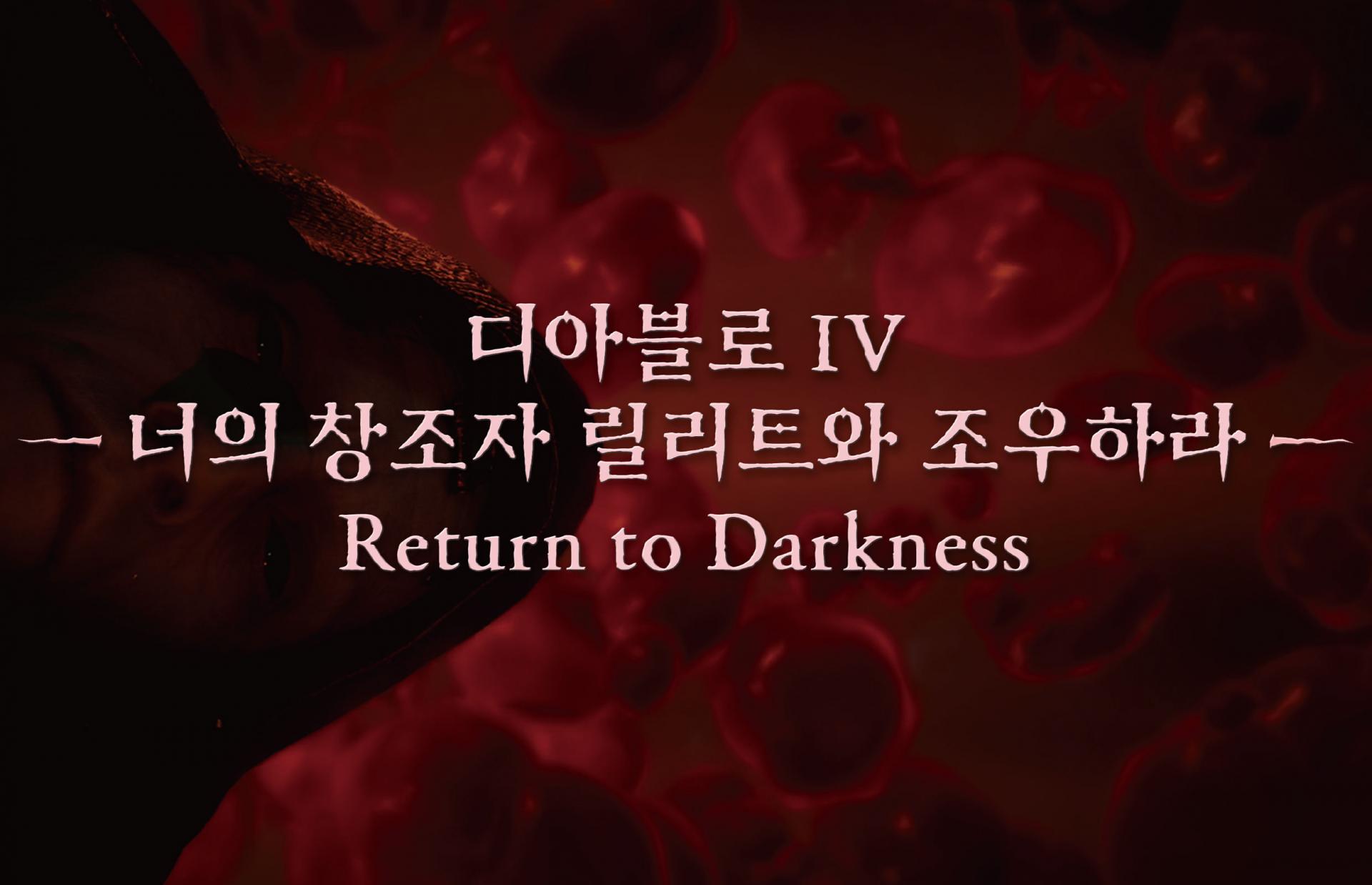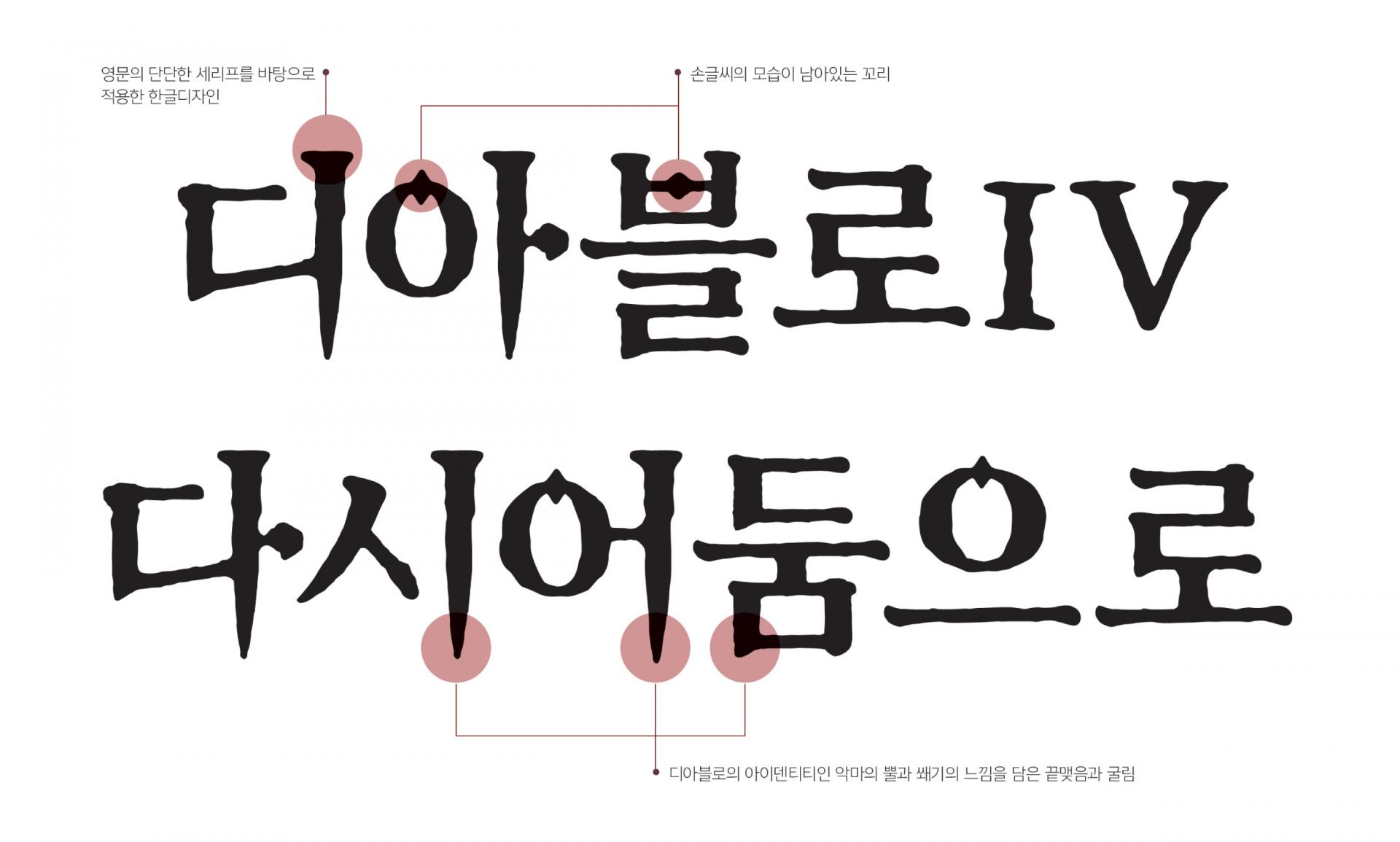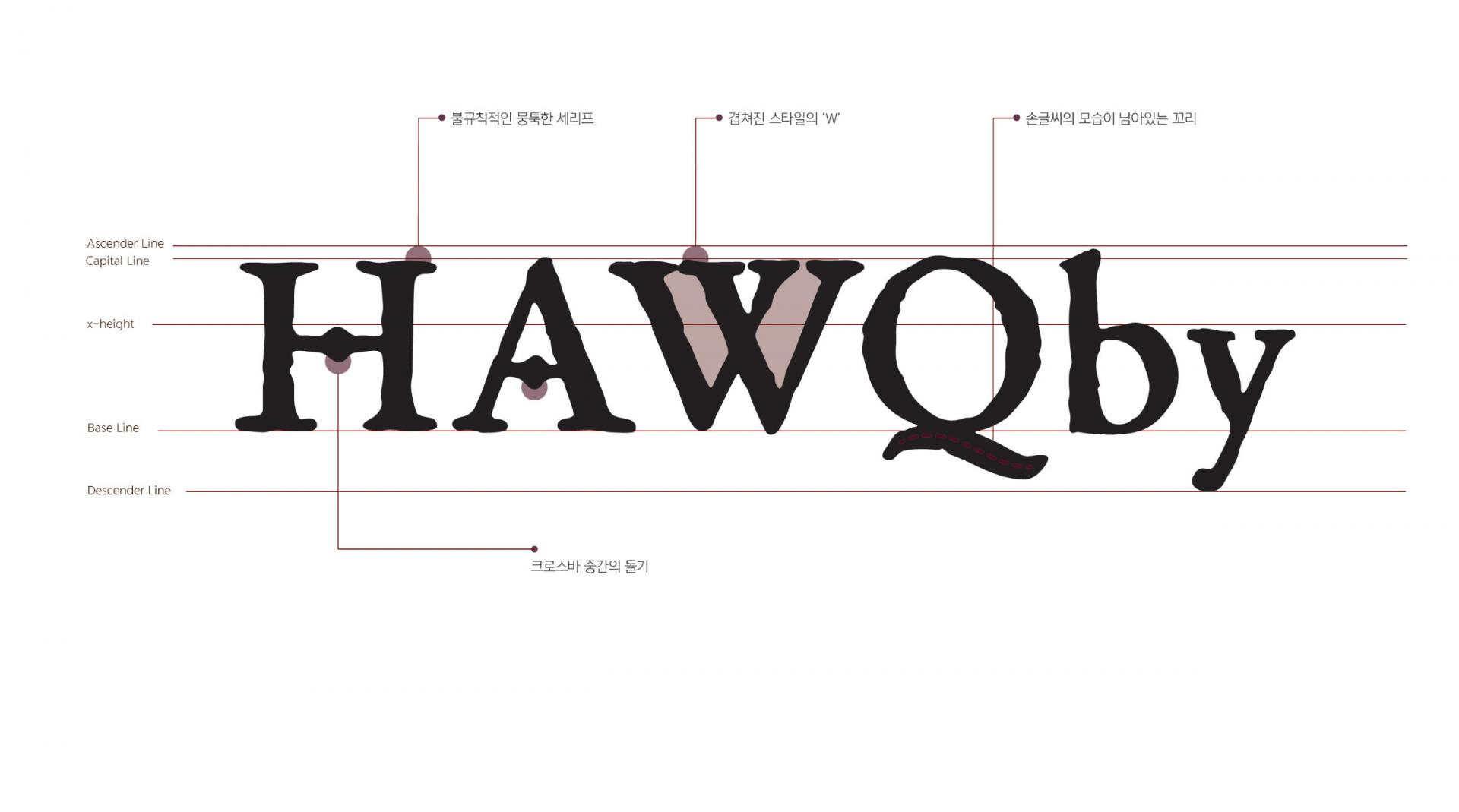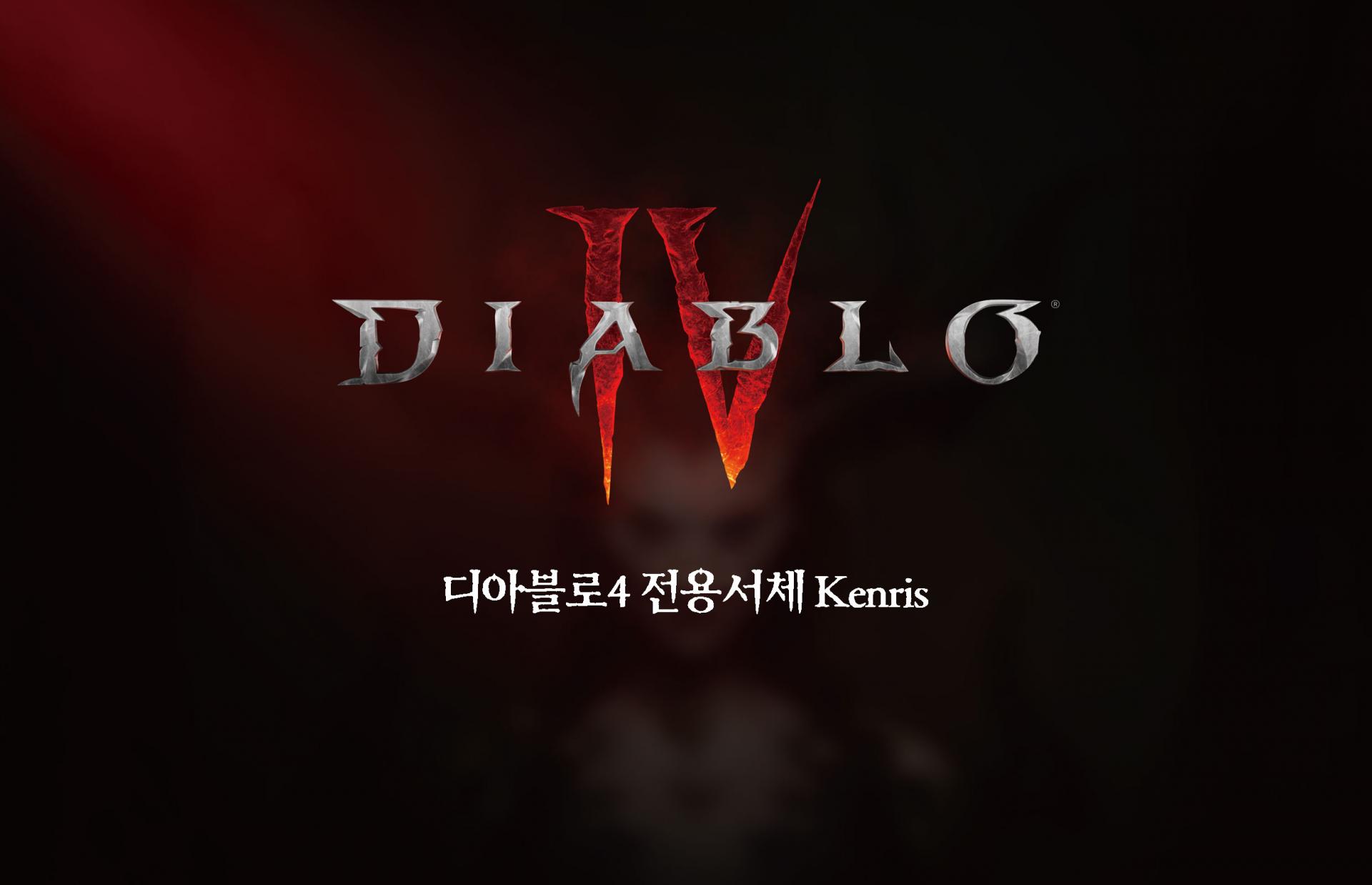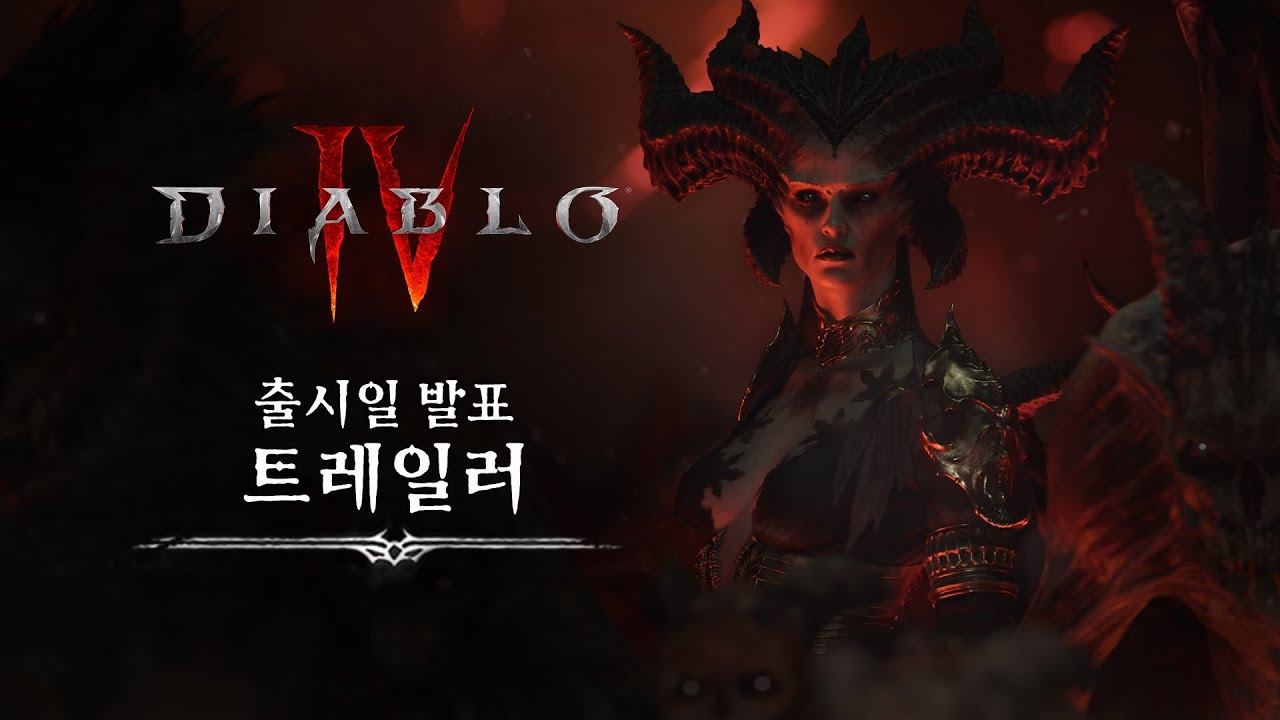
블리자드 엔터테인먼트 디아블로IV [kenris]
게임 '디아블로IV'의 전용서체 [Old fenris]를 바탕으로 모티프와 브랜드 아이덴티티를 강화할 수 있는 한글 서체를 제작했다. 세리프의 모양, 획의 디테일, 게임의 특징이 잘 반영될 수 있도록 디자인하였으며, '어둠의 성역'과 '증오의 악마'를 디자인 요소로 적용하여 디아블로IV의 세계관에 잘 매칭되도록 하였다.